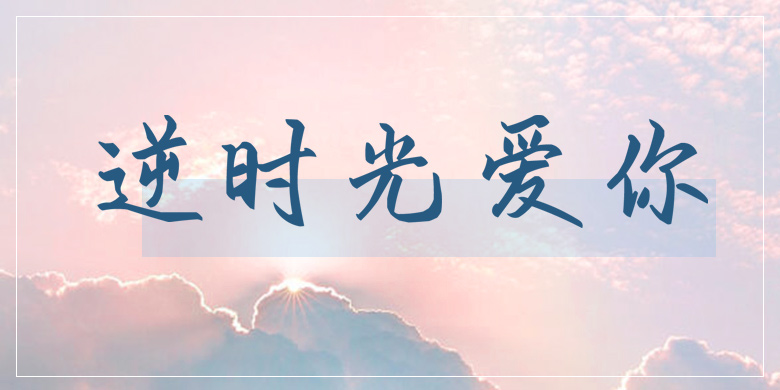
方正手迹-逆时光爱你
方正手迹-逆时光爱你,这款字体结构工整、笔画清晰,兼顾美观与易读性,适用于标题、正文、海报、包装、LOGO 等多种场景。字形优雅稳定,风格百搭耐看,适配日常排版与创意设计,让文字呈现更舒适、更具质感。方正手迹-逆时光爱你一笔一画,皆是细节,以均衡的比例、流畅的线条打造舒适视觉体验,字形端正大气,风格简约现代。无论是商业设计、品牌宣传还是日常排版,都能轻松驾驭,让文字更有格调与力量。方正手迹-逆时光爱你字体下载。
逆时光爱你这款字体的笔法结构皆源自传统书法,巧妙的将传统书法与现代审美相结合,整体风格娟秀淡雅且文艺气息十足,让人赏心悦目。适用于现代诗歌、短文印刷、文艺类的书刊、品牌广告和产品包装设计、综艺影视字幕,以及社交网络的个性化用字。